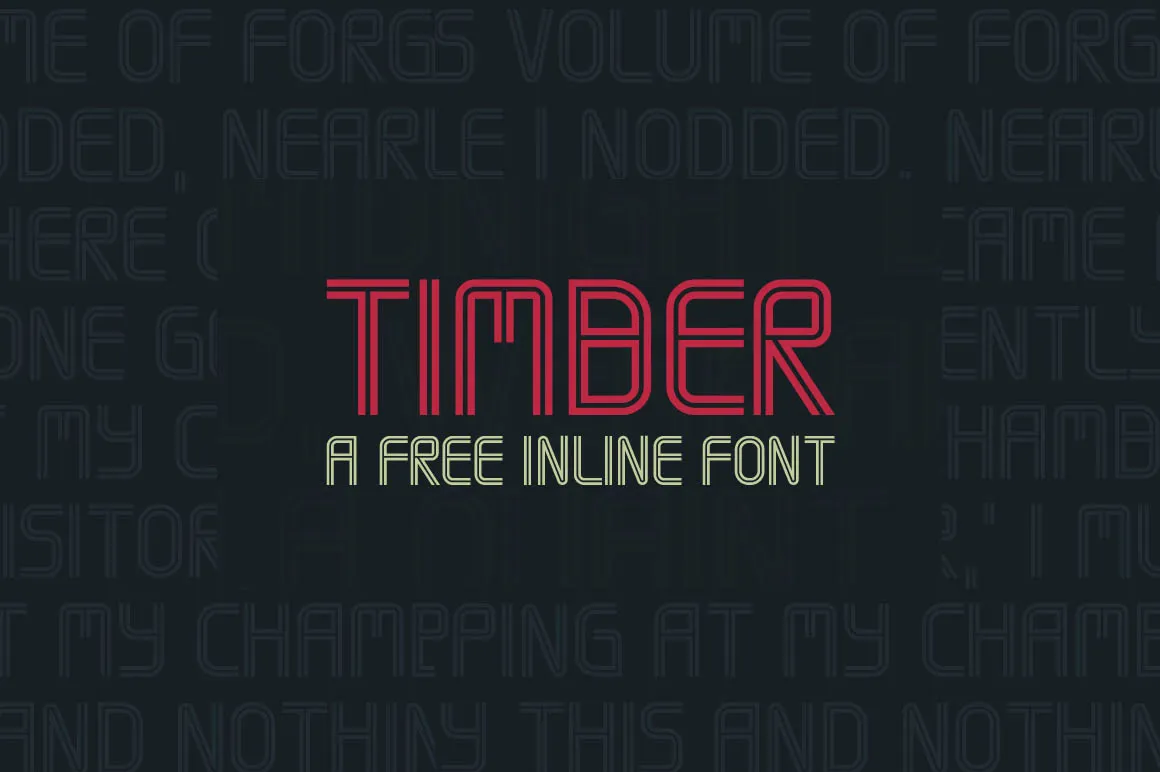
Timber Font – Download Grátis
A Timber Font é uma criação da Tugcu Design Co., obra-prima de um designer profissional que vai se adequar perfeitamente a diversos projetos de design digital e impressão. Ela é ideal para criar marcas, websites ou logomarcas, além de oferecer flexibilidade na sua aplicação com a possibilidade de ser convertida em fonte web. A proposta da Timber Font é trazer um estilo imponente e robusto, perfeito para quem busca uma fonte que transmita confiança e força. Esta fonte foi pensada para se adaptar às necessidades dos mais diversos projetos digitais, garantindo não apenas visual impactante, mas também facilidade na sua utilização em ambientes web. Com o Timber Font, você pode explorar a versatilidade desta fonte de design, sem comprometer a integridade ou os direitos autorais. É uma escolha ideal para quem busca um elemento gráfico que transmita força e robustez, adaptando-se tanto às criações digitais quanto aos projetos impressos.